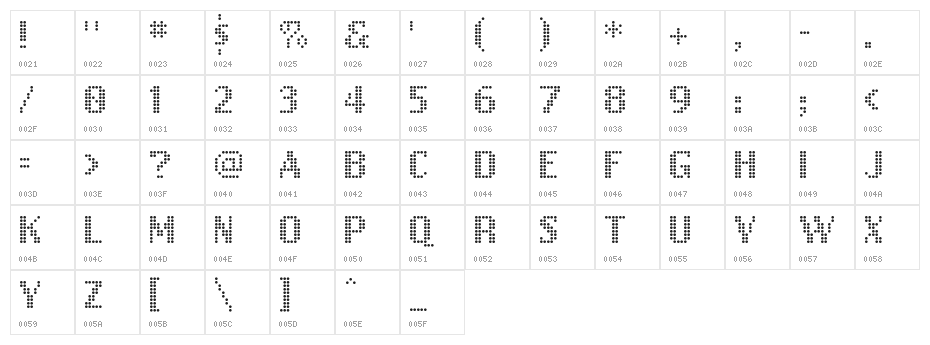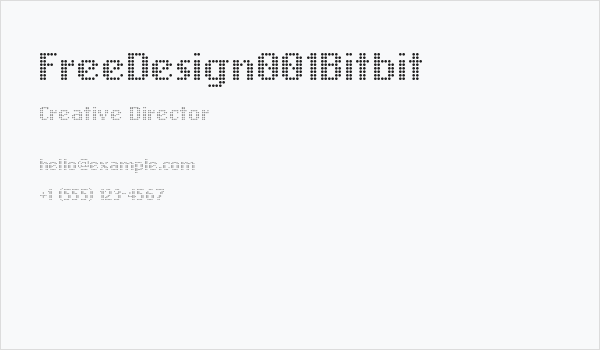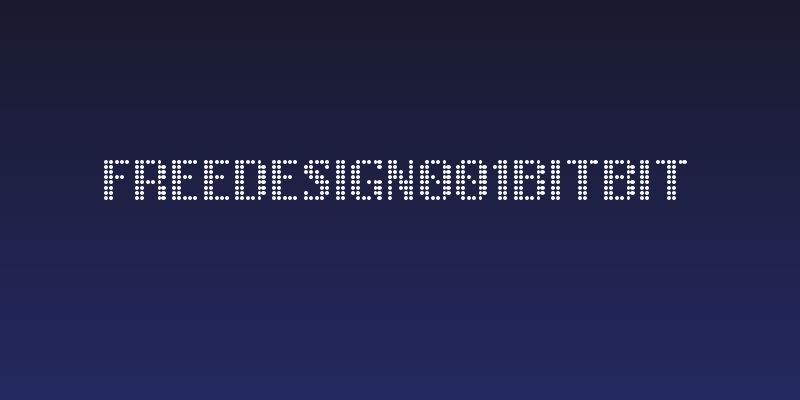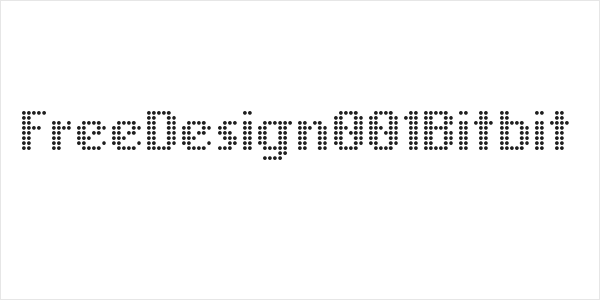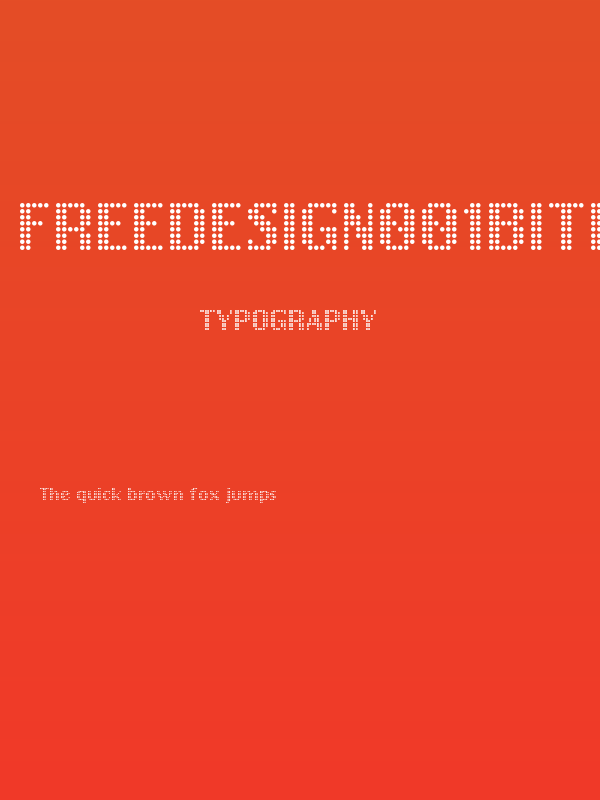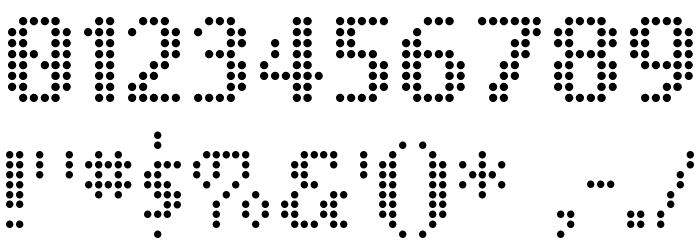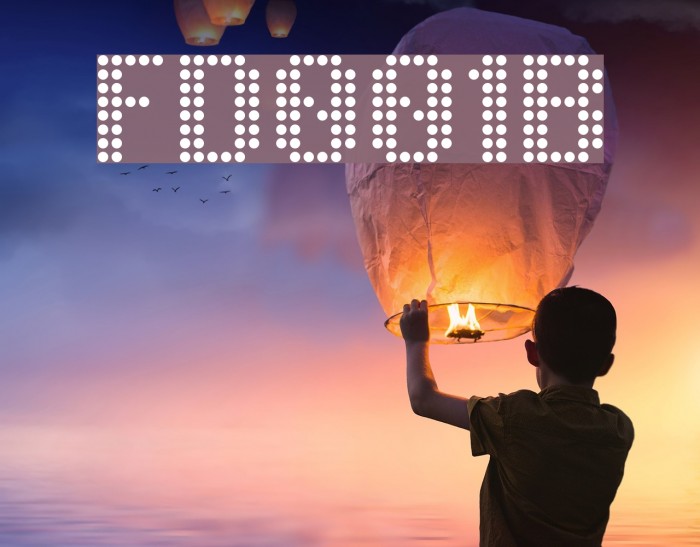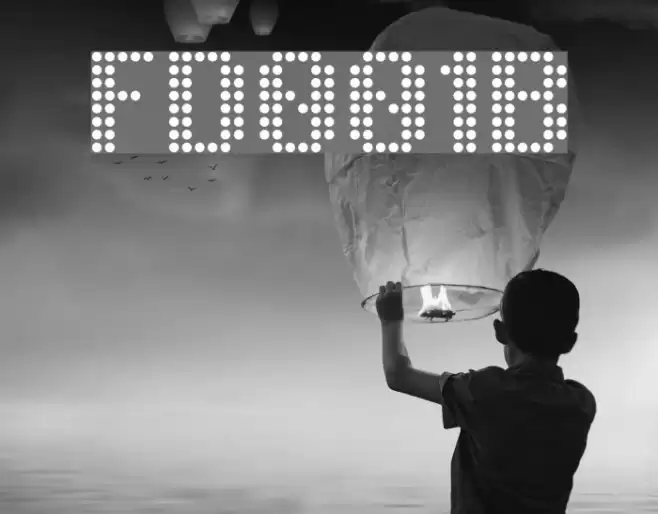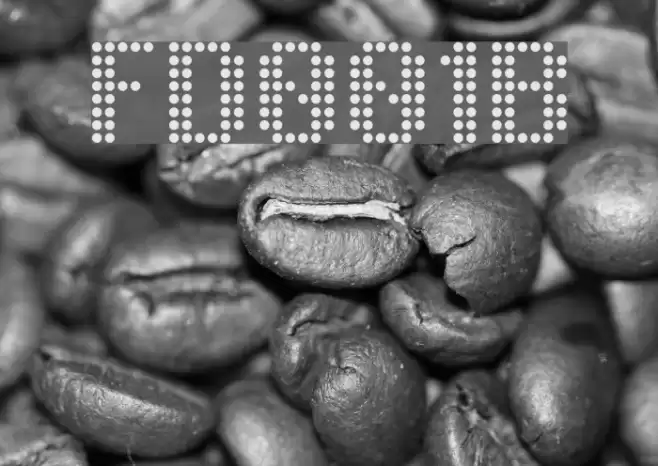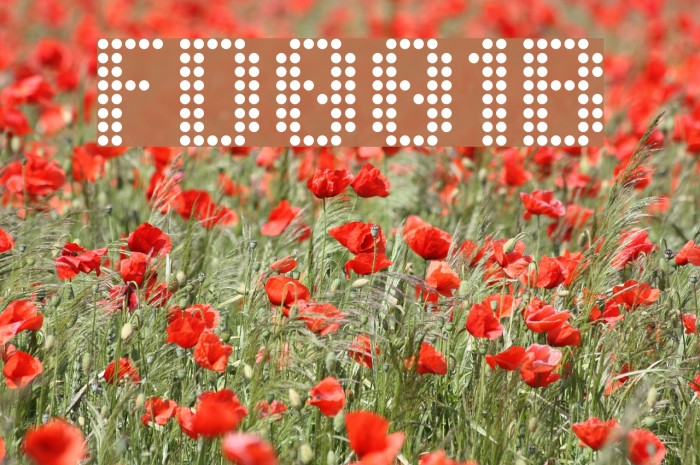
FreeDesign001Bitbit Font
| Cas d'utilisation | Headlines, Logos, Digital Displays |
| Projets proposés | Ideal for digital displays, tech-themed designs, retro gaming graphics, and creative posters. |